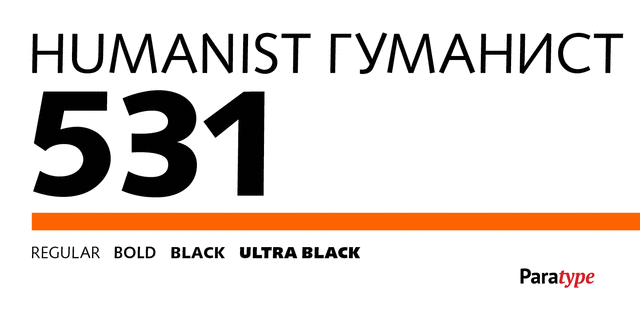
Версия фирмы Bitstream шрифта Syntax фирмы Stempel, 1968 (дизайнер Ганс Эдуард Майер). Неконтрастный гуманистический гротеск с оптически равными по толщине штрихами, повторяющий композиционную схему шрифтов старого стиля эпохи Ренессанс. Вертикальные штрихи наклонены вправо на 1 градус. Предназначен для применения как в текстовом, так и в акцидентном наборе. Кириллическая версия разработана в фирме ParaType в 1998 (дизайнеры Исай Слуцкер, Манвел Шмавонян).